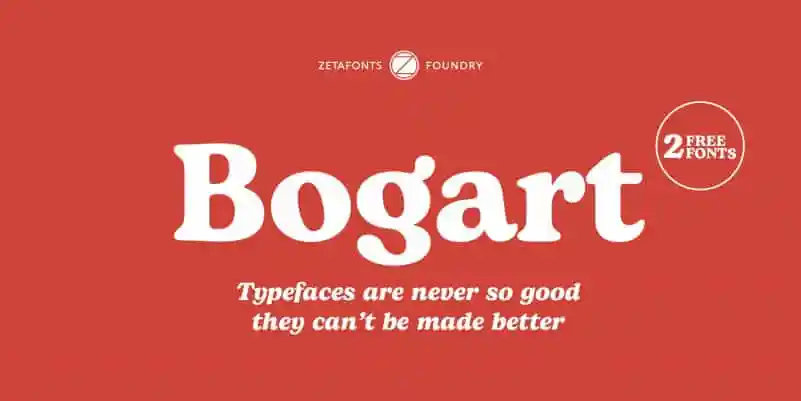
Bogart Serif Font Family
A Bogart Serif Font Family é uma herança elegante e moderna do estilo serífer que surgiu no final dos anos 1960 e início dos 70, época em que as tecnologias de gravação por transferência ruborizavam os textos, tornando-os populares nas culturas da moda e artes visuais. Essa fonte foi projetada em homenagem às faces do século XX como o Cooper Black (desenvolvido pela Bruce Cooper em 1922) e a Goudy Heavy Face (criado por Frederic W. Goudy e Sol Hess entre 1925-1932), que caracterizavam-se pelo estilo de face old style com um contraste baixo, dando um ar atemporal às letras. As formas da Bogart Serif Font Family são bem-humoradas e cheias de vitalidade, como se estivessem dançando em uma festa dos anos 60. Elas trazem caracteres florais que conectam o mundo do desenho à tipografia, criando um equilíbrio único entre a letra sem serif e os caracteres ornamentados. Este é um tipo de fonte perfeito para ambientes de design visual contemporâneo, especialmente adequada para aplicativos visuais atemporais ou para criar texturas vibrantes para campanhas publicitárias que desejam manter uma atmosfera nostálgica e alegre.